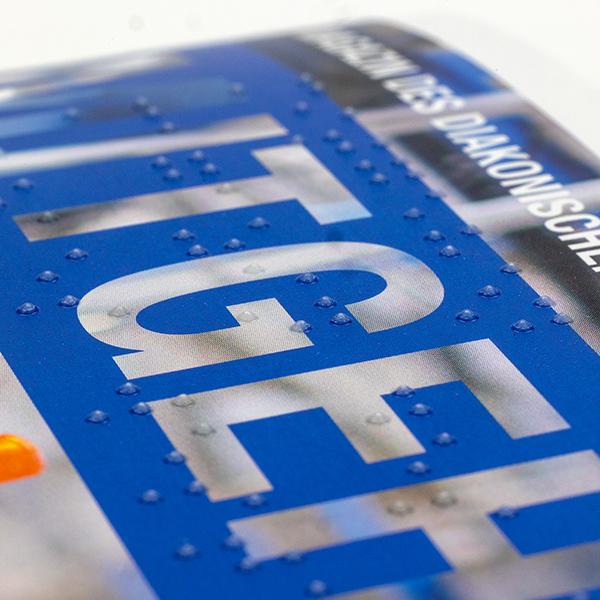
Braille-Schrift-Font und Anwendung
Ich glaube ich suche mir jetzt einen kommerziellen Anbieter der mit den einen Satz normgerecht absetzt und zahle dafür.
Ich hatte neulich ein Magazin zu setzen und habe den Titel in Braille (Basis-Schrift) einfach darüber gesetzt, außerdem einen kleinen Minikurs mit ein paar Buchstaben und Worten für Sehende. Ich habe die Zeichen per Hand gesetzt ohne Font, nach den üblichen Schriftgrößen laut Detailtypografie. Ich hatte aber jemanden, der die Ausdrucke kontrollieren konnte weil er noch 5 % Sehkraft hat. Produziert wurde später mit Braille-Lack im Siebdruck, eine feine Sache.
Von Kurzschrift hab ich jetzt nach Absprach mit einer blinden Bekannten Abstand genommen. Vollschrift – also Basisschrift plus einige Lautzeichen – bekommt man mit den besagten Online-Tools hin. Offen ist gerade noch ob auf Groß-Klein-Schreibung verzichtet werden kann.
Ich hab jetzt endlich einen Anbieter der den Satz korrekt übersetzt. Groß-Klein-Schreibung ist laut dem Anbieter eher unüblich.